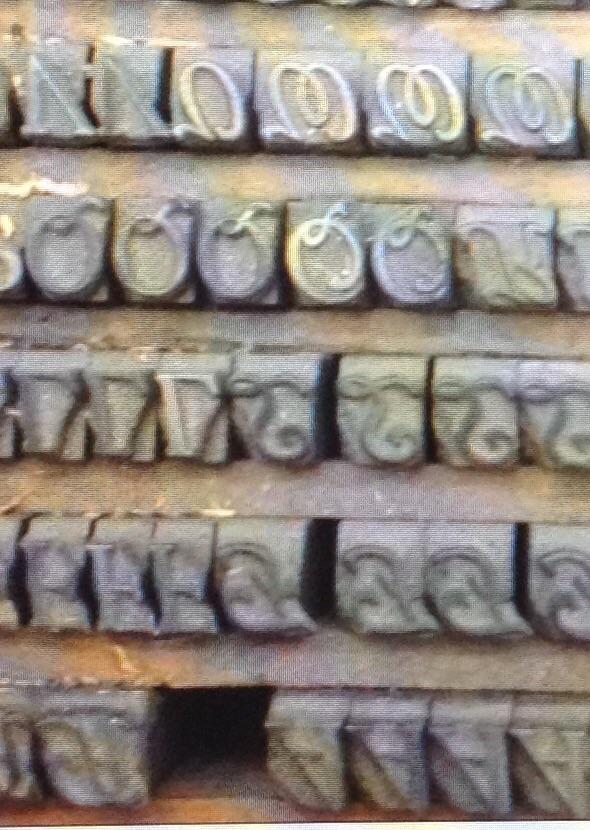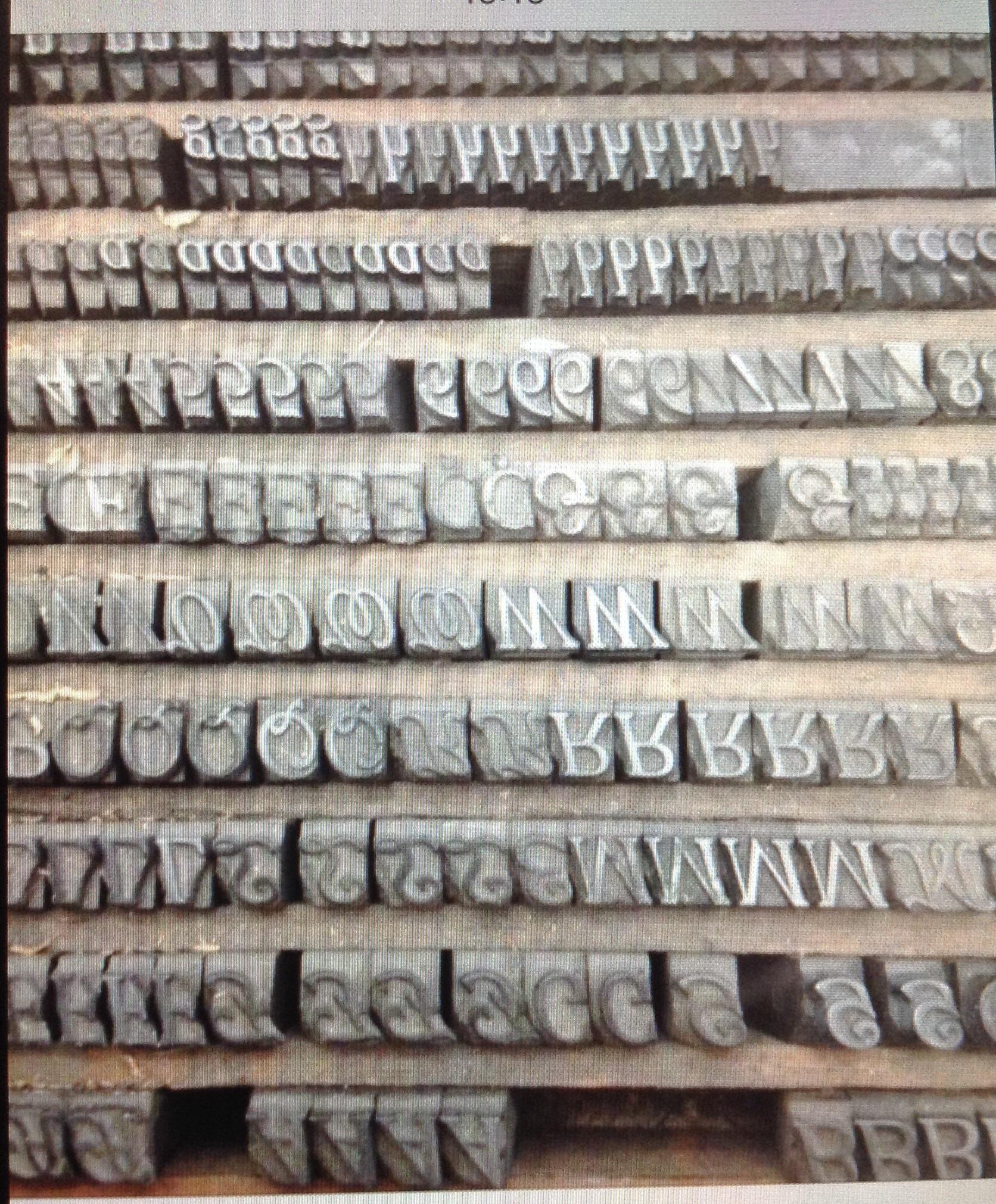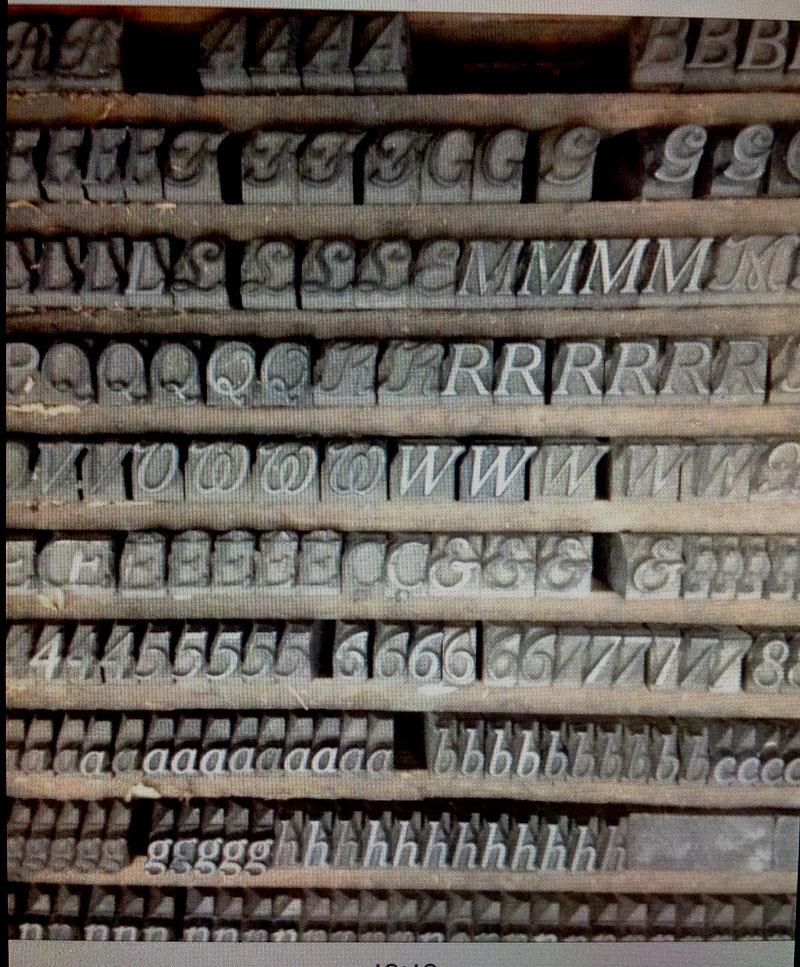
Setzkasten mit 2 Schriftschnitten
in alten Setzkästen zweier Buchdruckereien haben wir dies hier gefunden -- handelt es sich hier um 2 verschiedene Schriften oder eine Schrift mit 2 Schnitten?
Ich hab leider nur den halben Kasten (und das mit einem alt-öddeligen Handy) fotografiert. Wenn ich nur halbwegs wüsste, nach welchem Namen ich gucken müsste, würd mir das die Suche erleichtern...
Es sind mit Sicherheit Zierversalien im kursiven Schnitt. Die Ziffern sind allerdings verfischt.
Die Typen mit Überhängen sollten gedreht werden, sonst brechen bei größeren Kastenbewegungen die Überhänge ab.
Es ist tatsächlich die "Cheltenham" – @RobertMichael: vielleicht sehen die Schwunglettern anders aus, weils Bleiguss ist oder kursiv? – jedenfalls: Vielen Dank an alle, die geguckt haben !